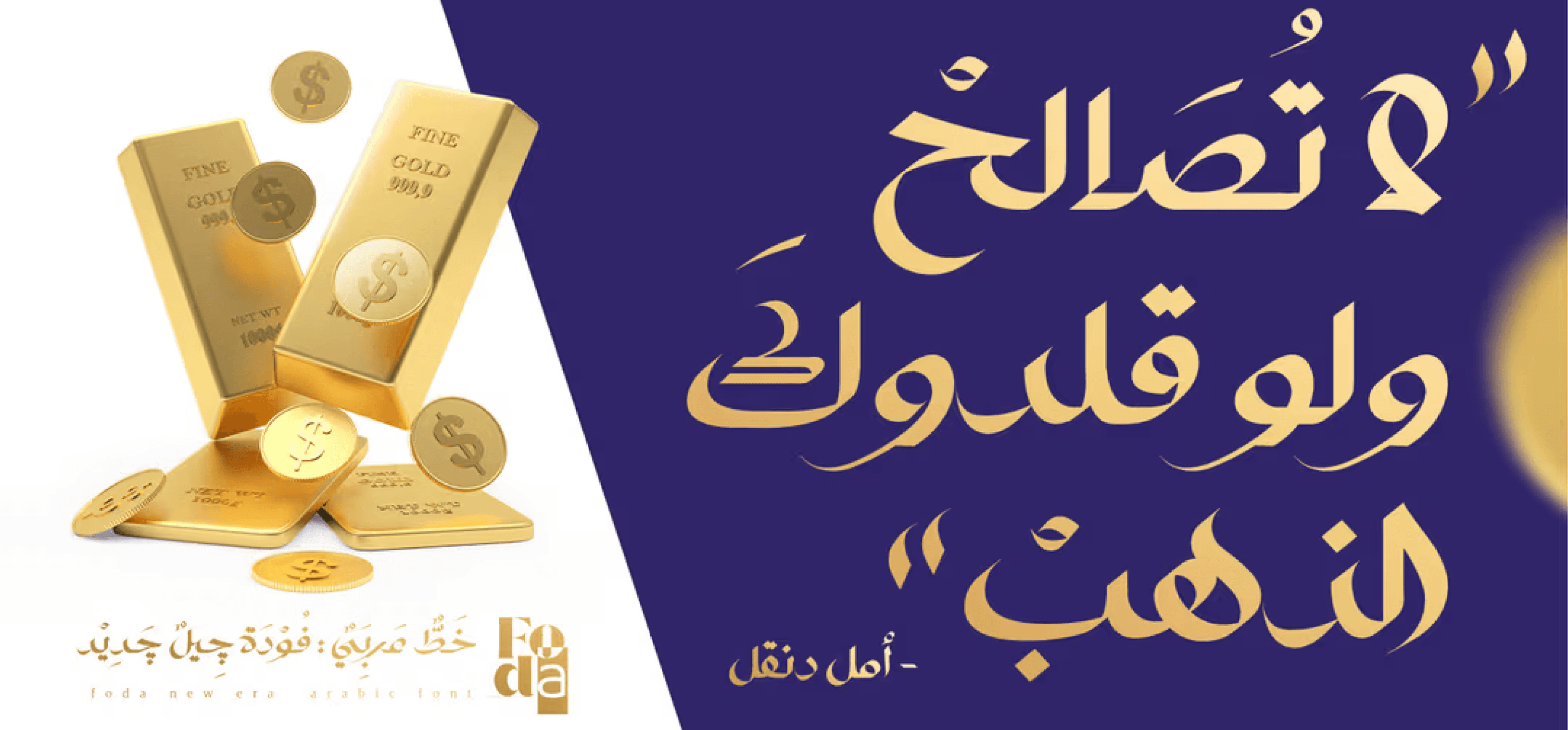
هو خط عربي عصري بأسلوب الخطوط اليدوية، مناسب للعلامات التجارية، الشعارات، التغليف، الإعلانات، تصاميم وسائل التواصل الاجتماعي، الملصقات، والمزيد.
يدعم الخط أيضًا حروف العرض اللاتينية (Display Latin Glyphs) لتوفير توافق كامل في التصميمات متعددة اللغات.